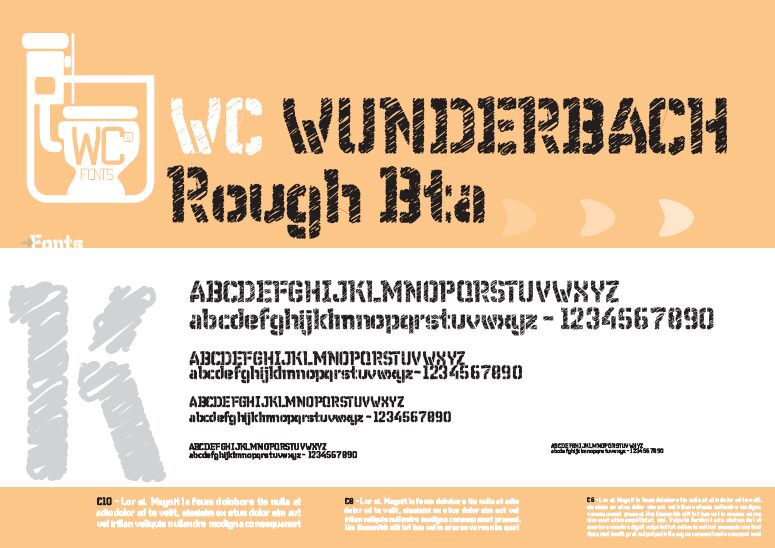
WC Wunderbach Rough Bta od WC Fonts to darmowy, wyszczerbiony krój akcydensowy zbudowany z grubych, odręcznych pociągnięć. Jego nierówne krawędzie i porysowane wnętrza przypominają napisy wypełnione suchym markerem. Kształty wydają się surowe i niespokojne.
Plakat muzyczny to dla niego najbardziej przekonujące środowisko, a surowa faktura nawiązuje do kserowanych grafik i niezależnej grafiki muzycznej w stylu DIY. Sprawdza się również w gadżetach deskorolkowych, tytułach gier niezależnych i nieformalnej identyfikacji wizualnej wydarzeń, ponieważ nieregularne formy wyglądają na zrobione ręcznie, a nie złożone z czcionek. Ten krój sprawdza się najlepiej wtedy, gdy same napisy mają zapewnić surową, bazgroloną powierzchnię projektu, zamiast pełnić rolę czystego podpisu.